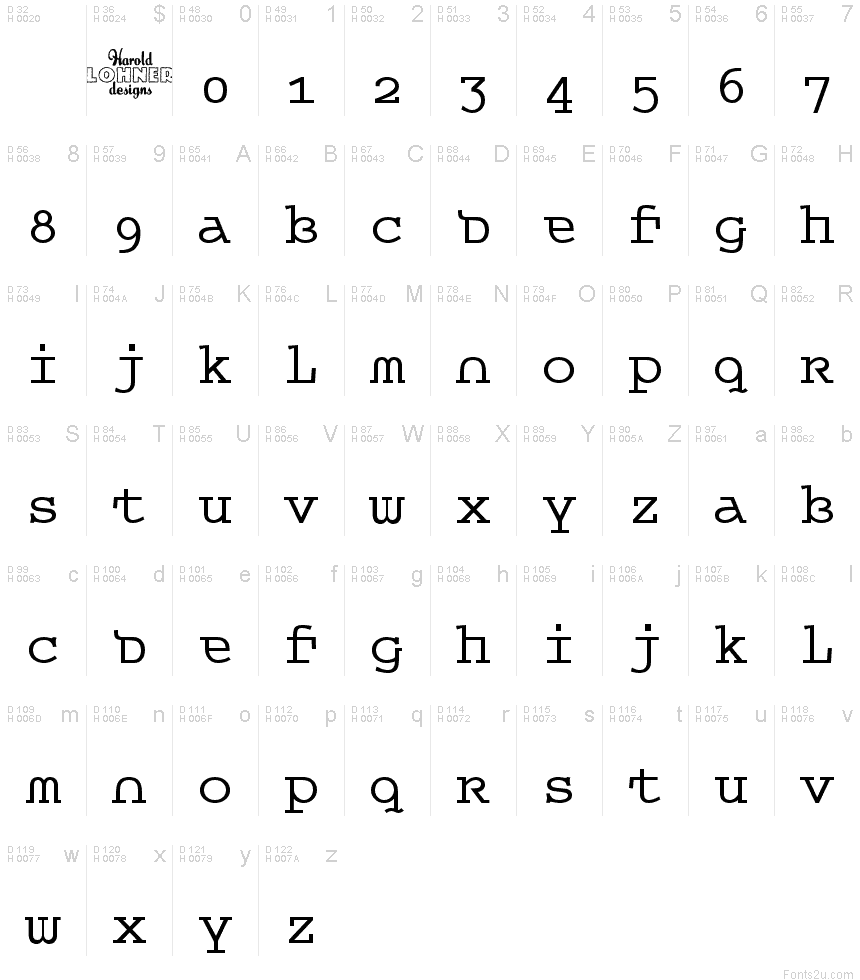
Queer Theory di Harold Lohner è un font display retro gratuito con le atmosfere lounge della fine degli anni '60 e dell'inizio degli anni '70. Le lettere abbinano tratti spessi e arrotondati ad alcune curve ingegnose – specialmente la q con il cappio e la r con l'uncino – rendendo il carattere complessivo morbido, anticonvenzionale e un po' teatrale, piuttosto che rigorosamente geometrico.
È ideale per poster, copertine di album, branding di boutique, titoli di riviste e cartelli, dove si desidera un giocoso richiamo d'epoca senza sfociare nella piena psichedelia. Essendo un font gratuito, funziona bene anche per brevi titoli, loghi e iniziali in stile monogramma, poiché le sue forme ampie e i dettagli curvi conferiscono abbastanza carattere anche a poche lettere per reggere l'intero layout.